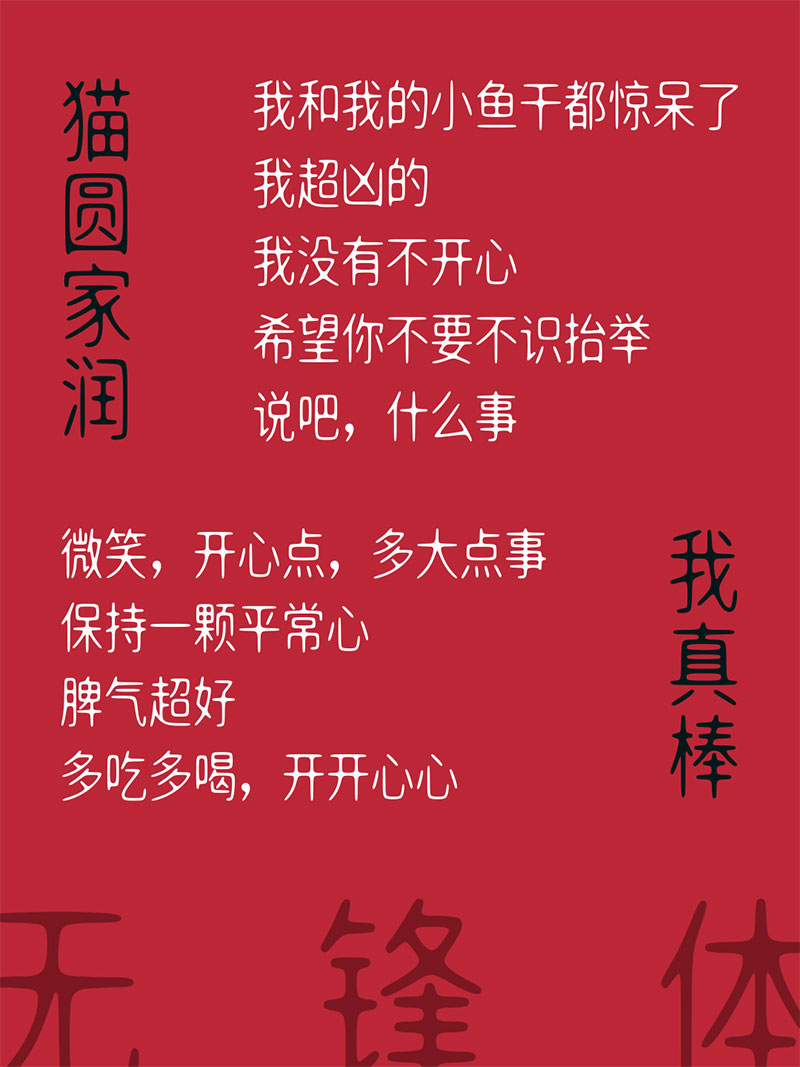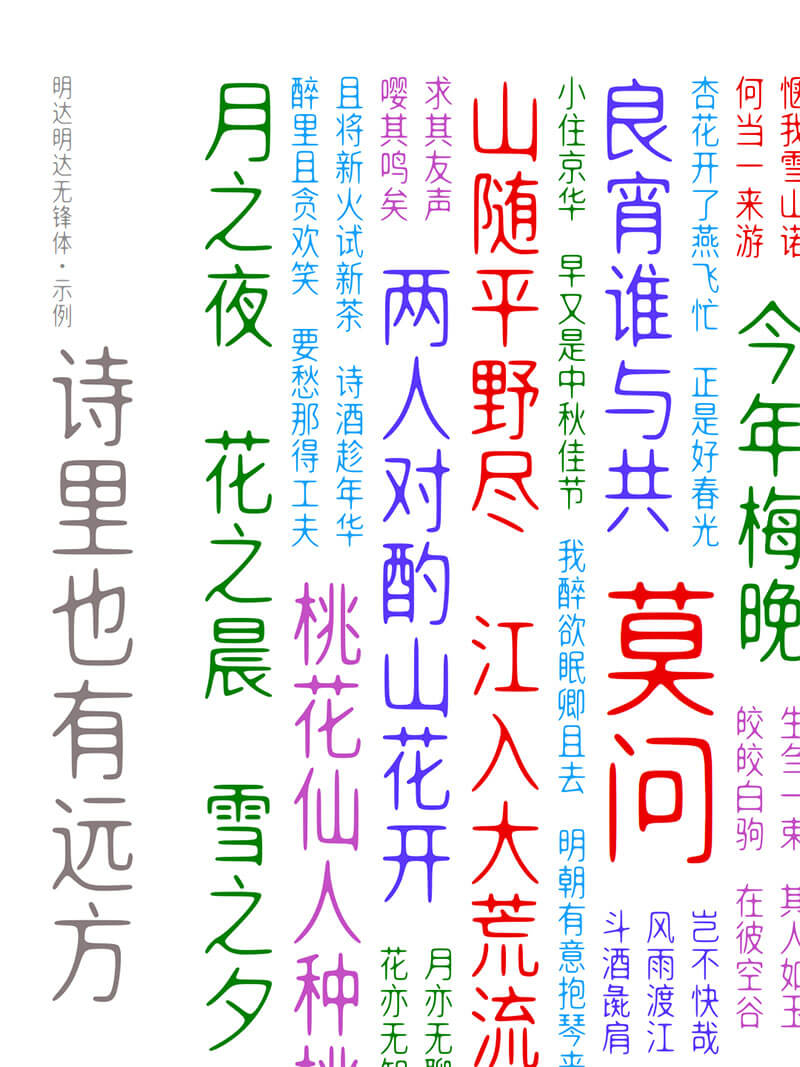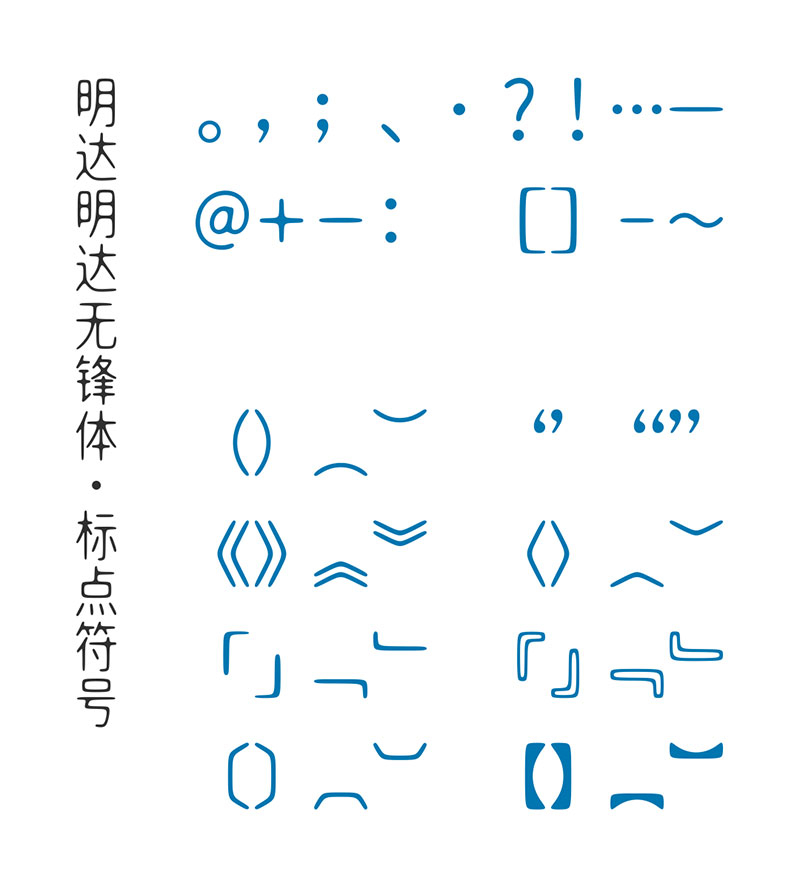
字符集合:包含GB2312中的6763个汉字和49个全角中文标点符号。(不含英文、数字)
字形特点:笔划布局上采用中宫放松的黑体布局。在大体布局上参考思源黑体(布局很均匀)和以前宣传画的各种竖型字体,根据具体笔划形态冲突、重心变化、美观平衡做调整。
似水的凝聚形成“墨的无锋”,浑圆无折角,无笔锋,故名“无锋体”。
字形特点:中宫放松,布局舒展,步进等宽;笔划略细,字身稍长,高:宽=5:4。